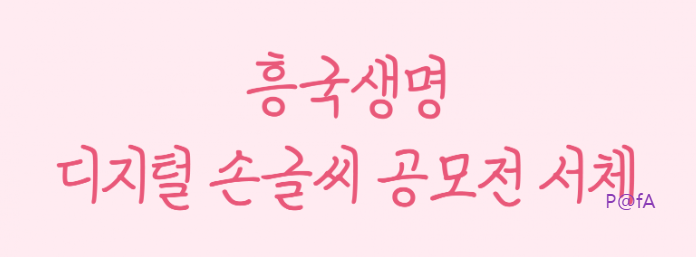
흥국생명에서 진행한 디지털 손글씨 공모전에서 수상한 글꼴인 전화선체를 무료로 다운로드하는 방법을 살펴본다. 더불어 누구나 무료로 사용이 가능한 전화선체를 컴퓨터에 설치하는 방법과 코딩 시에 사용하는 방법도 살펴본다.
누구나 개인적인 용도뿐만 아니라 상업적인 용도에도 무료로 사용할 수 있도록 제공하는 무료 글꼴인 전화선체를 소개한다. 전화선체는 흥국생명이 주최한 2021년 제1회 디지털 손글씨 공모전에서 최우수작으로 선정된 글꼴 중 하나이다. 이때 선정된 글꼴은 전화선체 이외에 이서윤체와 심경하체도 있는데, 다음에서 제시하는 순서대로 따라 하면 전화선체를 무료로 다운로드해서 사용할 수 있다.
위의 이미지에서 보듯이 전화선체는 자소가 자유로운 형태인 전형적인 손글씨 스타일을 고스란히 담고 있는 서체이다.
위에서 보듯이 전화선체는 자소에 일정한 규칙이 없이 자유로운 형태인 전형적인 손글씨 모양을 확인할 수 있다. 또한 아래에 설치 화면에서 확인할 수 있듯이 받침으로 사용된 자음이 오른쪽으로 밀려 쓴 듯한 다소 독특한 형태로 제작된 글꼴이다. 이러한 전화선체를 컴퓨터에 설치하는 방법은 매우 간단하다. 설치를 원하는 해당 파일을 누른 후에 나오는 팝업에서 설치 버튼을 눌러주면 된다.